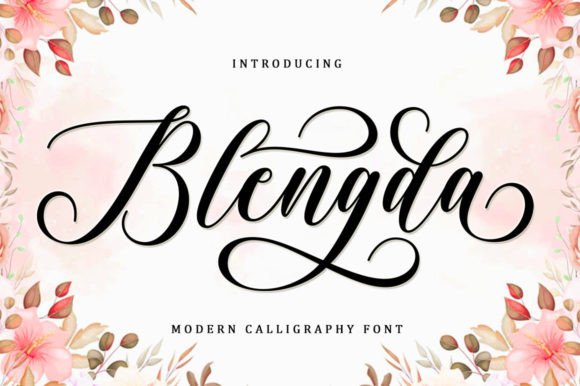
Blengda
Blengdaのような高品質の素材をお探しの場合、このプレミアムパッケージはクリエイティブなプロジェクトに素晴らしい選択です。
精密に作られたBlengdaは、クリーンなベクター、滑らかなタイポグラフィ、そして安心のための商用ライセンスを提供します。
POD(オンデマンド印刷)製品、結婚式の招待状、またはソーシャルメディアのグラフィックを作成している場合でも、Blengdaは理想的です。